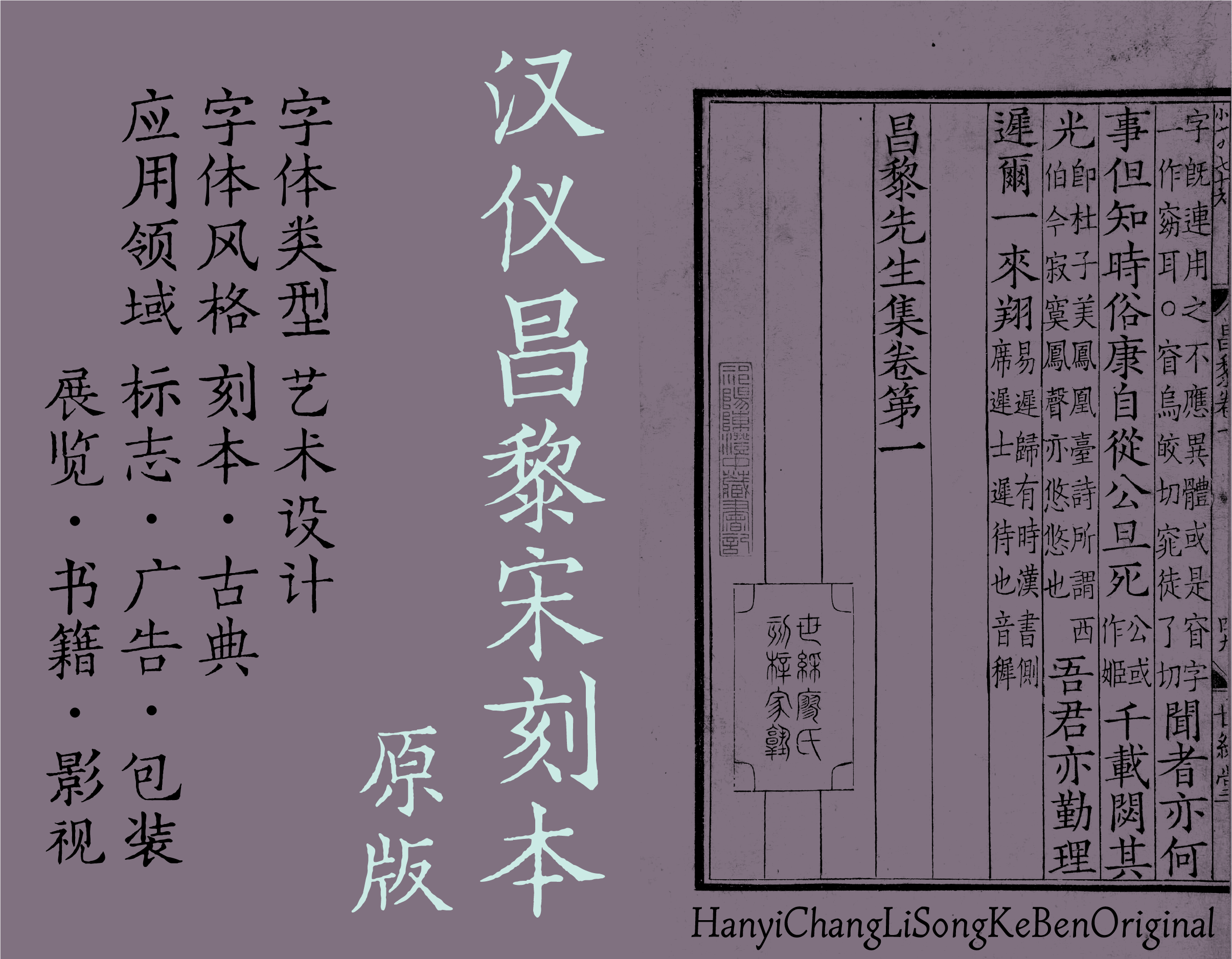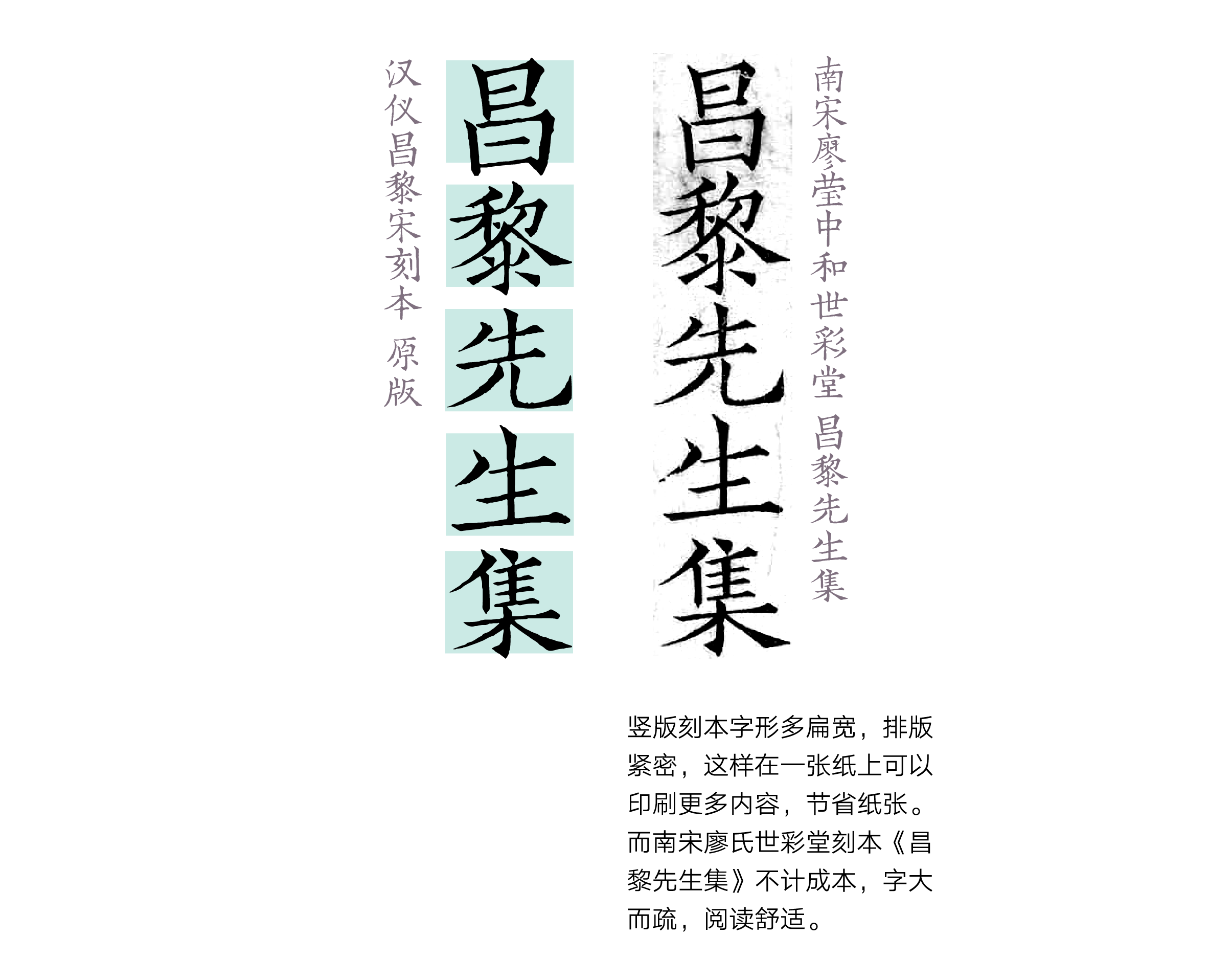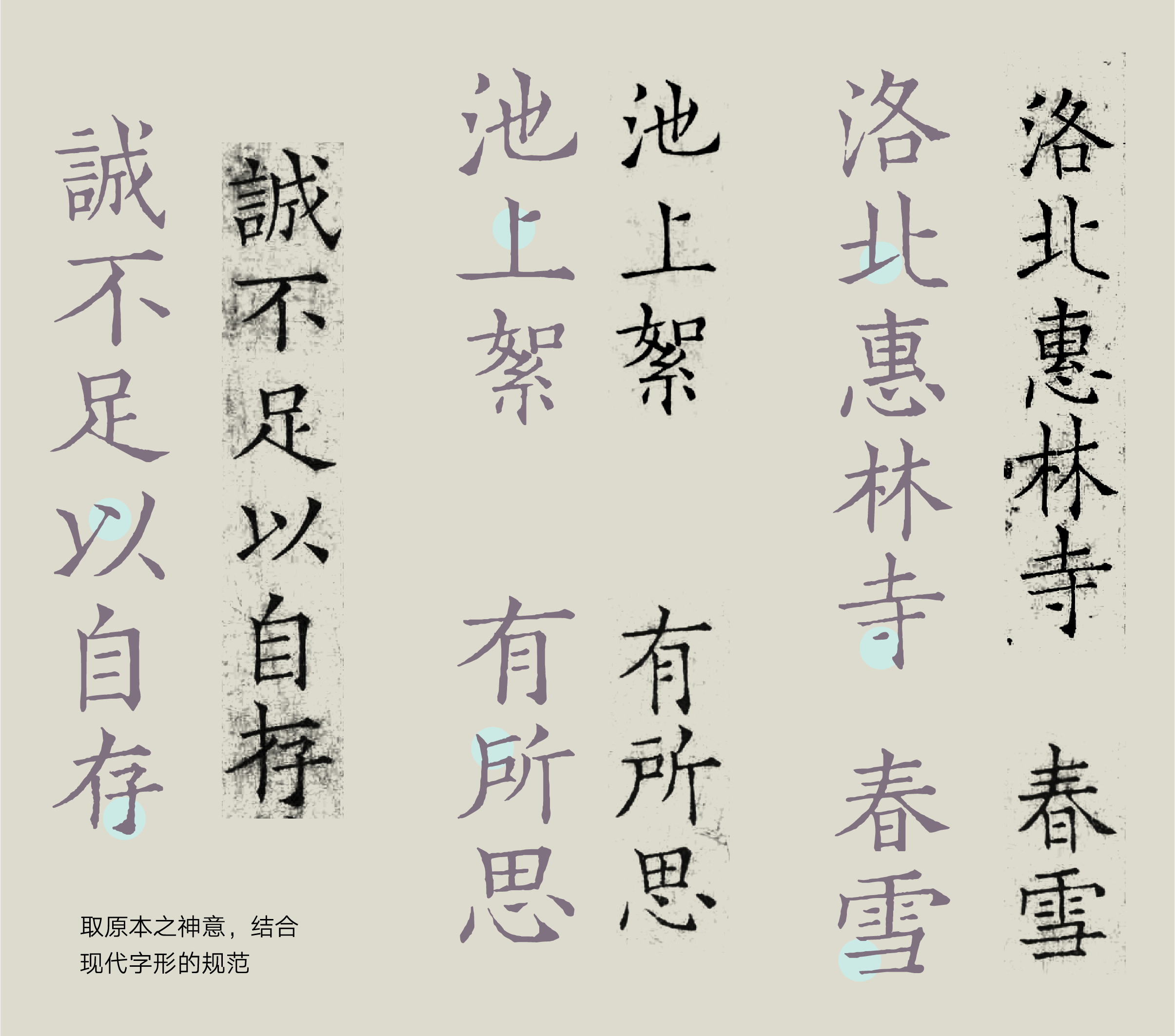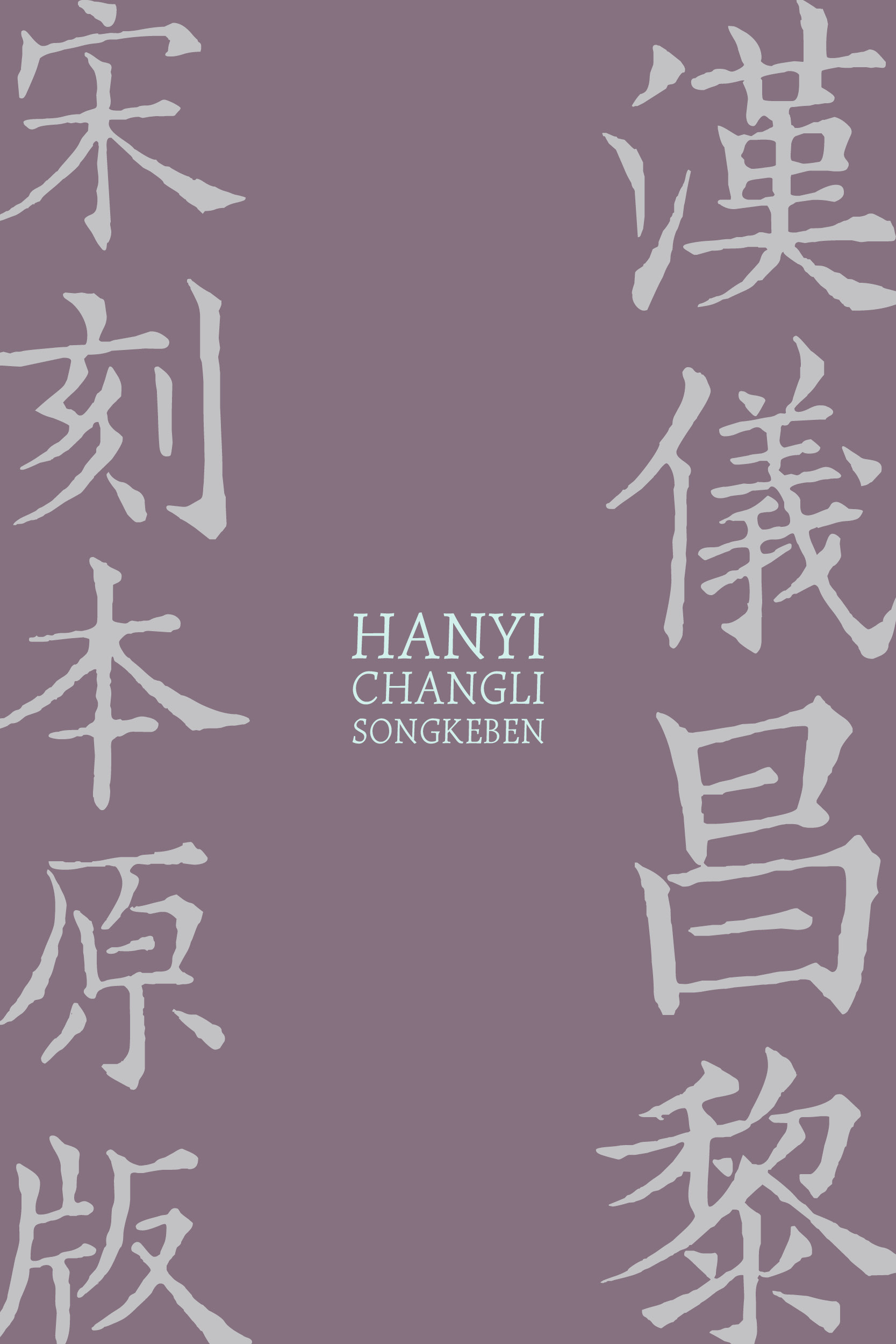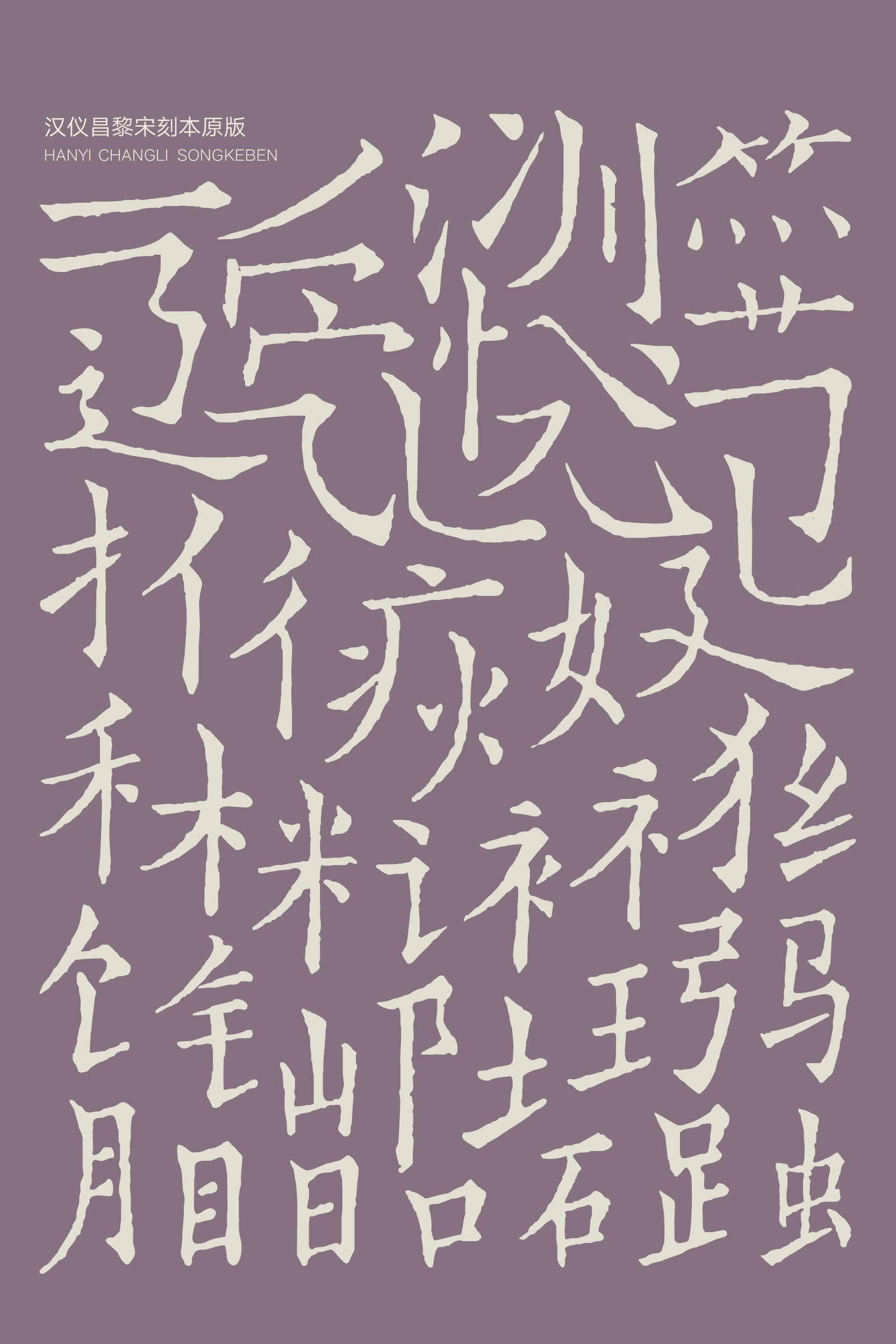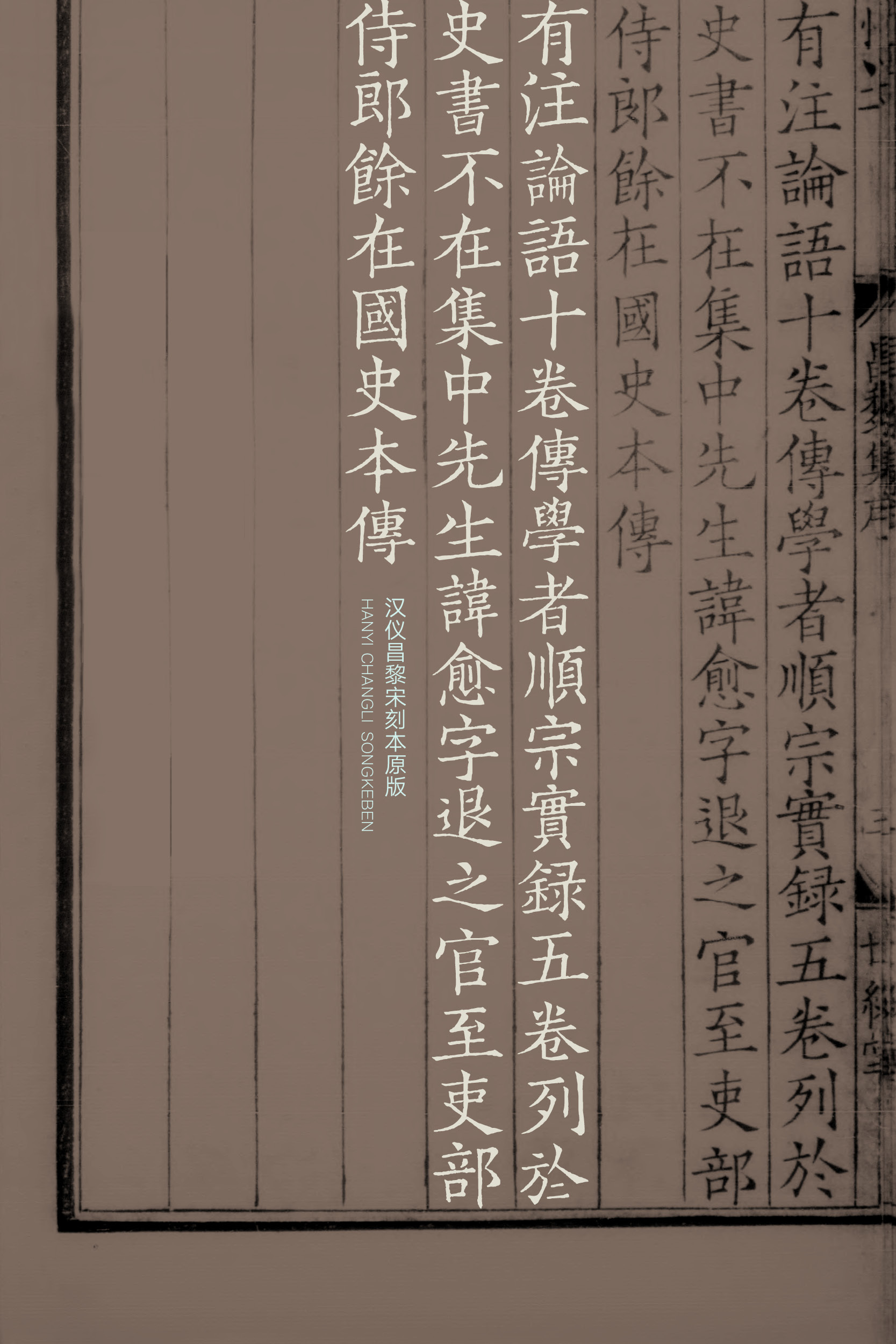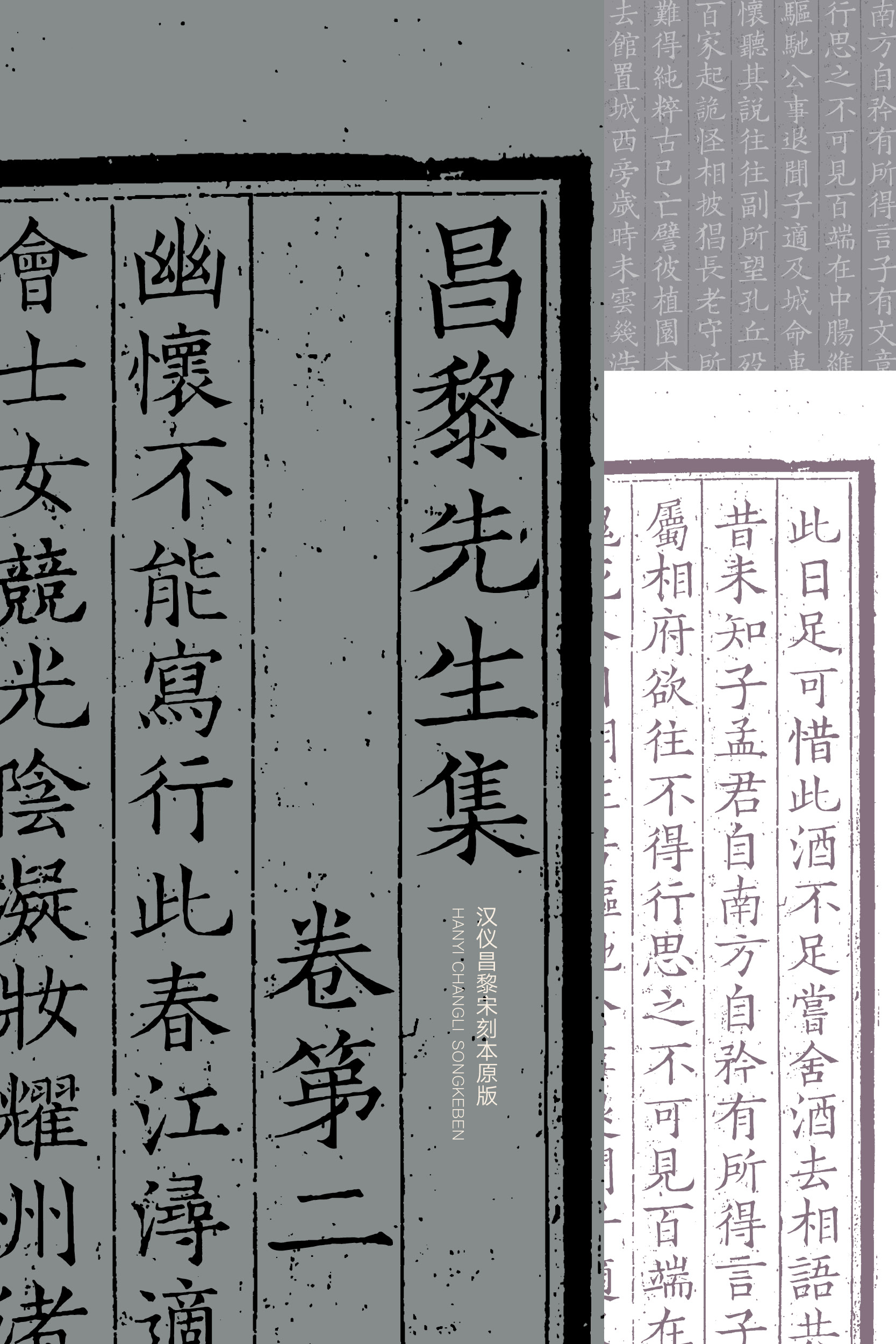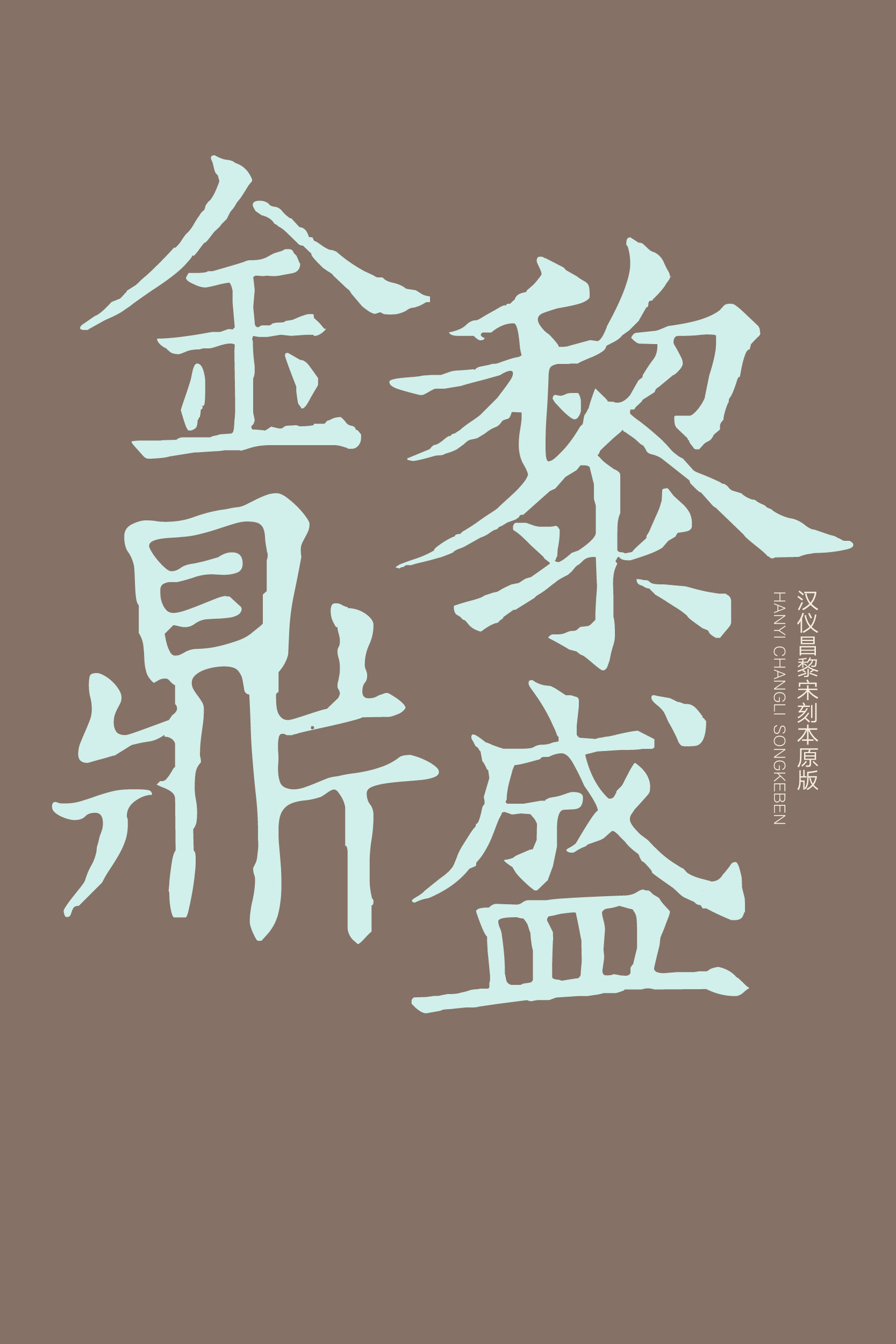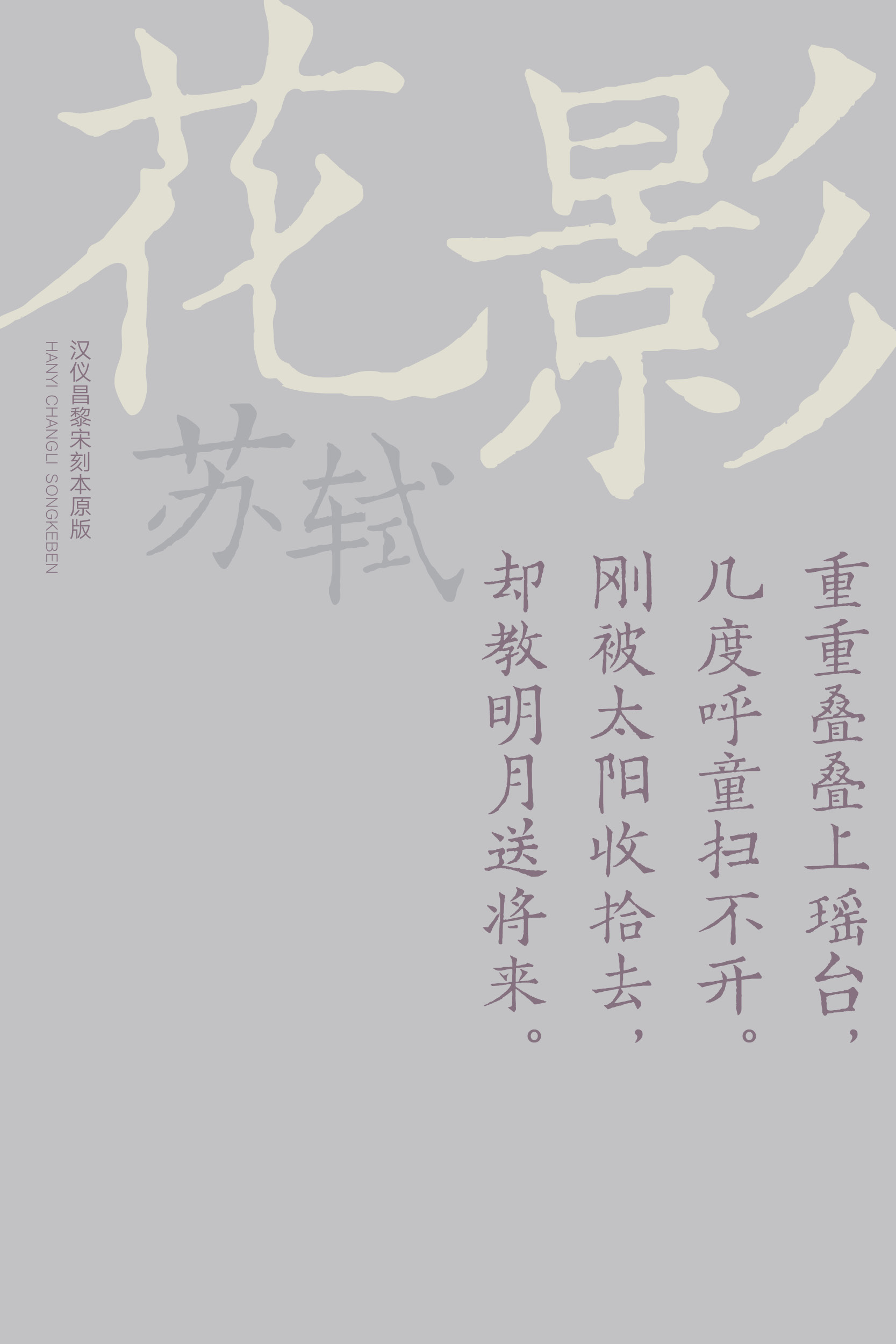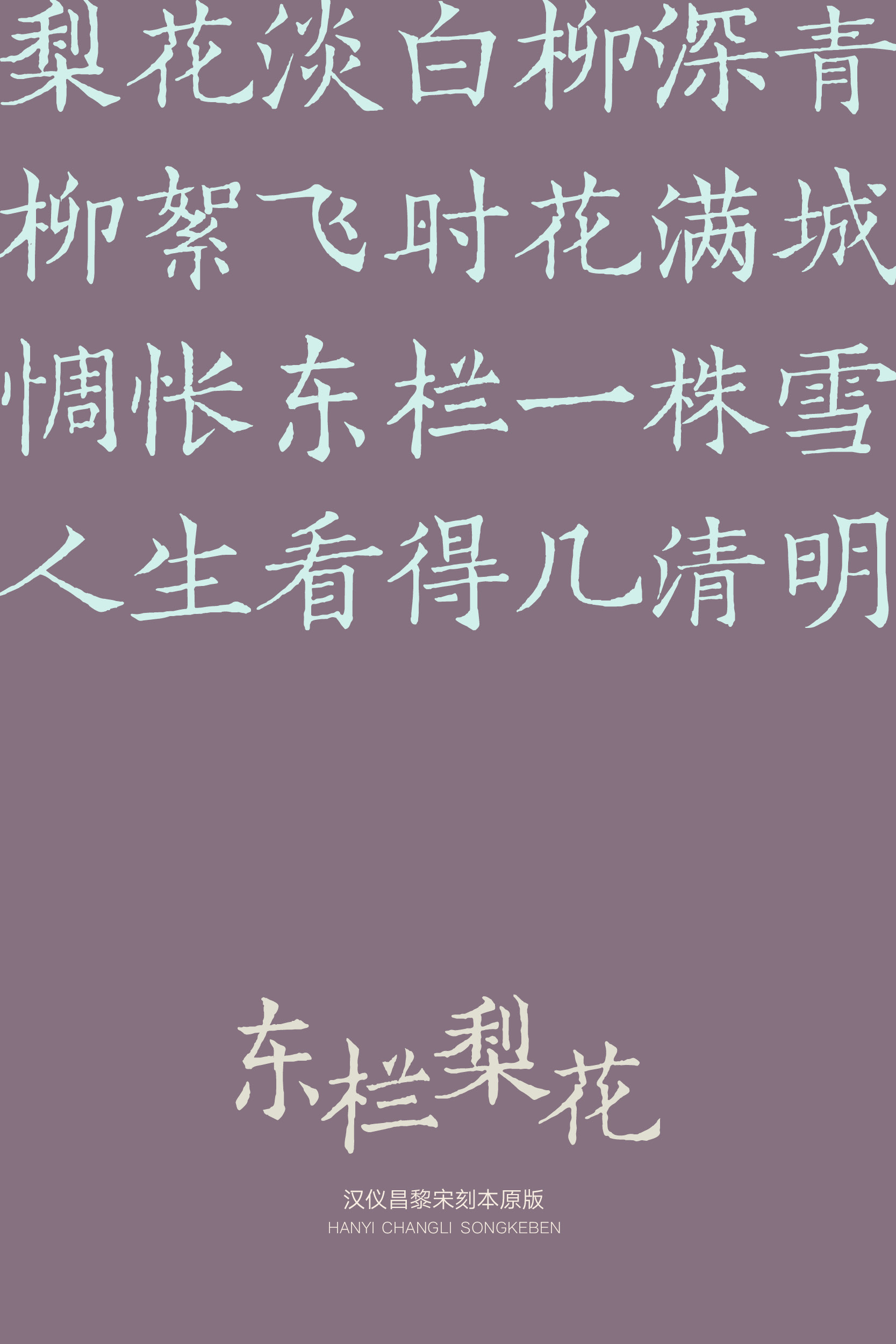
汉仪昌黎宋刻本原版
宋刻本存世极少,难得一见。
早在明朝,宋刻本已有“寸纸寸金”之说。而在珍稀的宋刻本之中,南宋时期廖莹中世彩堂刻本《昌黎先生集》被誉为「无上神品」。
南宋时期,都城临安(今杭州)成为重要的出版中心之一,西湖边上,廖莹中的世彩堂刻书技艺精湛、不计成本。
南宋时期廖莹中世彩堂刻本《昌黎先生集》所用书体隽秀,刀法精湛,排版疏朗,纸莹墨润,展示了宋代刻书出版的巅峰,具有宋版书“纸白如玉,墨黑如漆,字大如铜钱”的典型特征。此本诞生之后的800年间,辗转多位藏书家之手,现今孤本存世,藏于中国国家图书馆。
汉仪昌黎宋刻本,复刻于南宋时期廖莹中世彩堂刻本《昌黎先生集》,保留其神意,字型规正而略显扁宽,笔画纵横清晰,结构明朗疏正,工整严谨之中不失自然古趣。汉仪昌黎宋刻本分为两个版本:原版注重古韵趣味,保留原本几百年间历经的时间痕迹;精修版边缘顺滑齐整,对于字形细节的处理更为精炼细致。
宋刻本之美在于字体、在于版式。
宋刻本《昌黎先生集》所用书体具有浙刻气质,是兼有欧、柳体特征的楷体;排版疏朗,因而字形规整而略显扁宽。
取原本之神意,笔画纵横清晰,结构明朗疏正。
字形微微向右上倾斜,中宫收紧,重心上提,宋韵悠扬。
虽为刻本书体,但个别笔画留有断笔和牵丝,流露书法行笔之笔意。
汉仪昌黎宋刻本原版保留了原本几百年间历经的时间痕迹,古朴、坚韧,使得宋代刻书之美重新跃然纸上;另有汉仪昌黎宋刻本精修版,经过精心的调整,笔画曲线光滑平整,提升了排版阅读体验,适应更为广泛的现代应用环境。